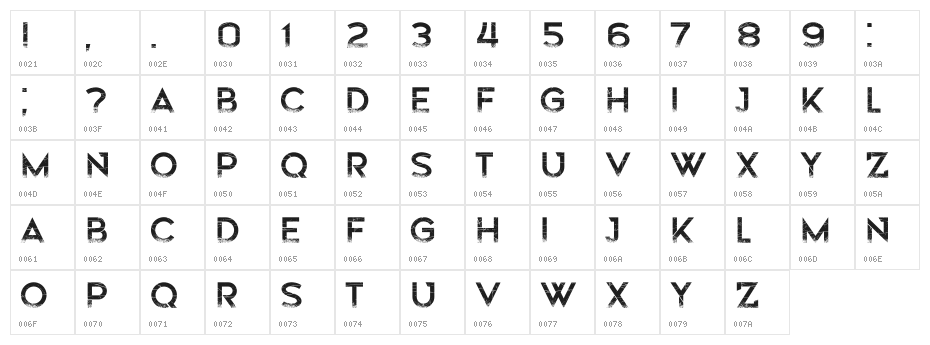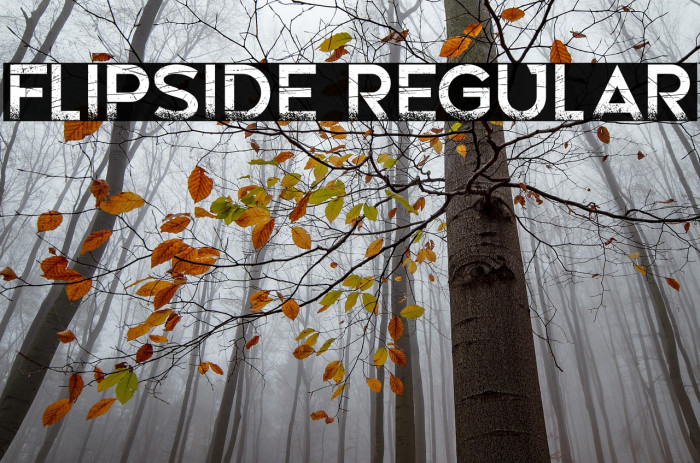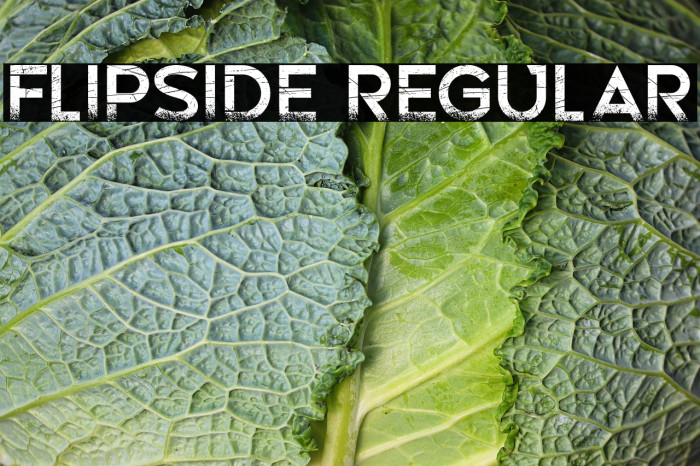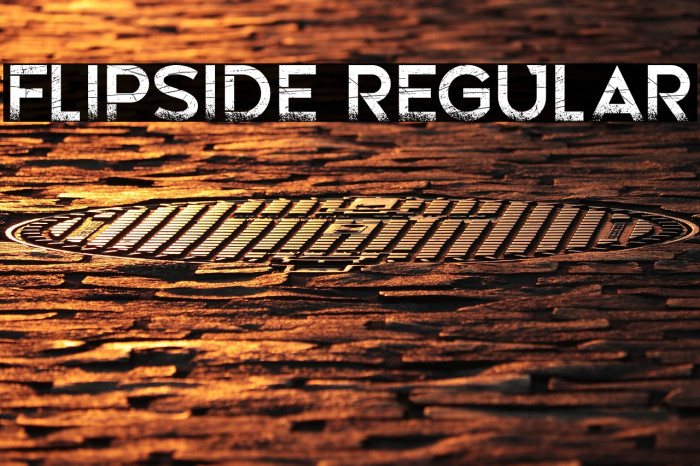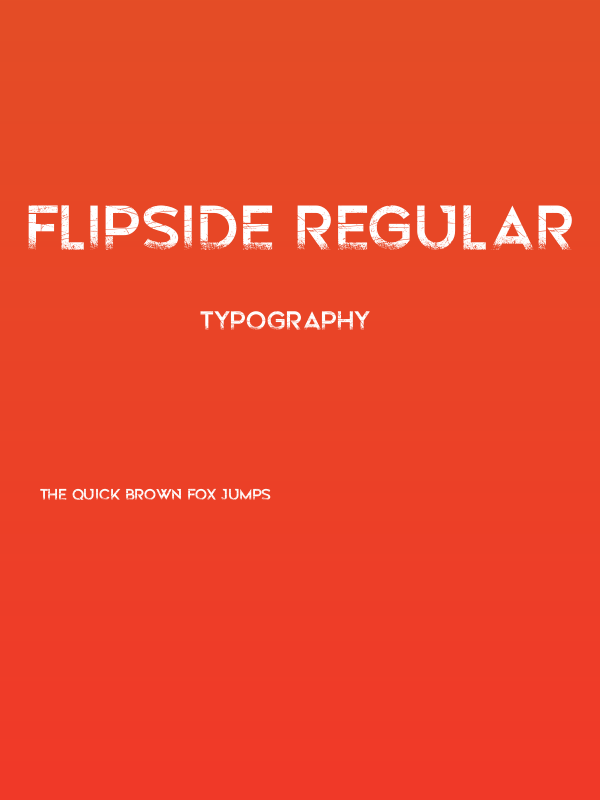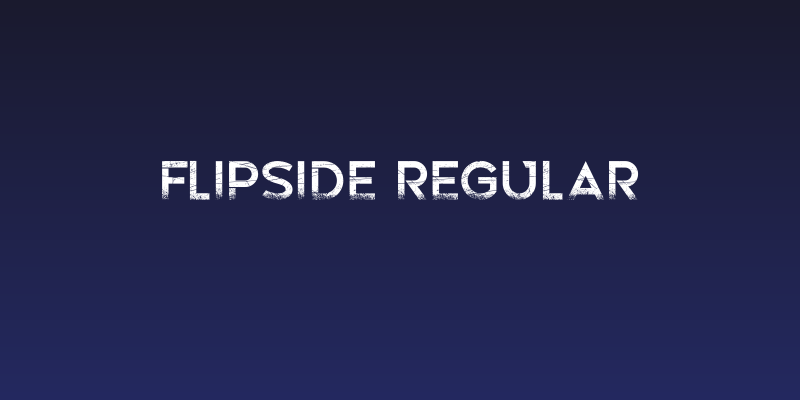
Flipside Regular Font
| الفئات | Messy |
| النمط العام | Vintage |
| مشاريع مقترحة | Ideal for posters, album covers, branding for vintage-themed products, and any design needing a rugged, historical feel. |